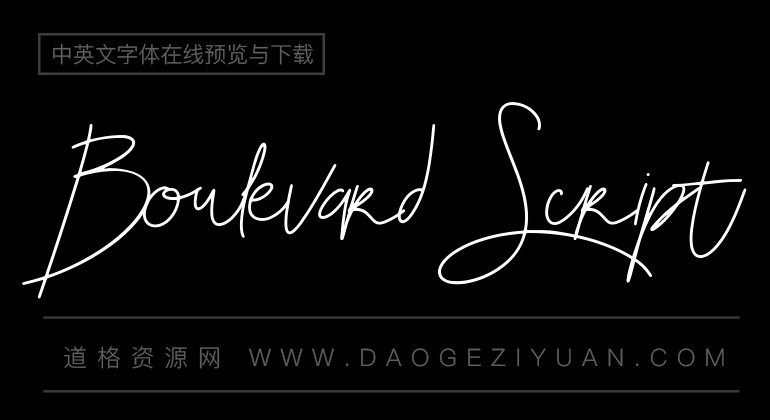
Boulevard Script
Boulevard Script 是一款以西方古典风格为基础的西文字体,由 Monotype Imaging 公司设计,其字体笔画自由流畅,具有浓郁的古典气息,适合用于装饰性的文字,如婚礼邀请函、海报、标识等。Boulevard Script 拥有 6 种字重,包括 Light、Regular、Medium、Bold、Heavy 和 Extra Bold,字体支持多种语言,兼容多种操作系统,可以在 Windows 和 Mac 上使用。
Boulevard Script是一款非常不错的手写艺术字体,具有很好的视觉感,适合于文化类的宣传设计、商业类品牌的广告和产品包装设计以及个性化文字排版等较多场景。